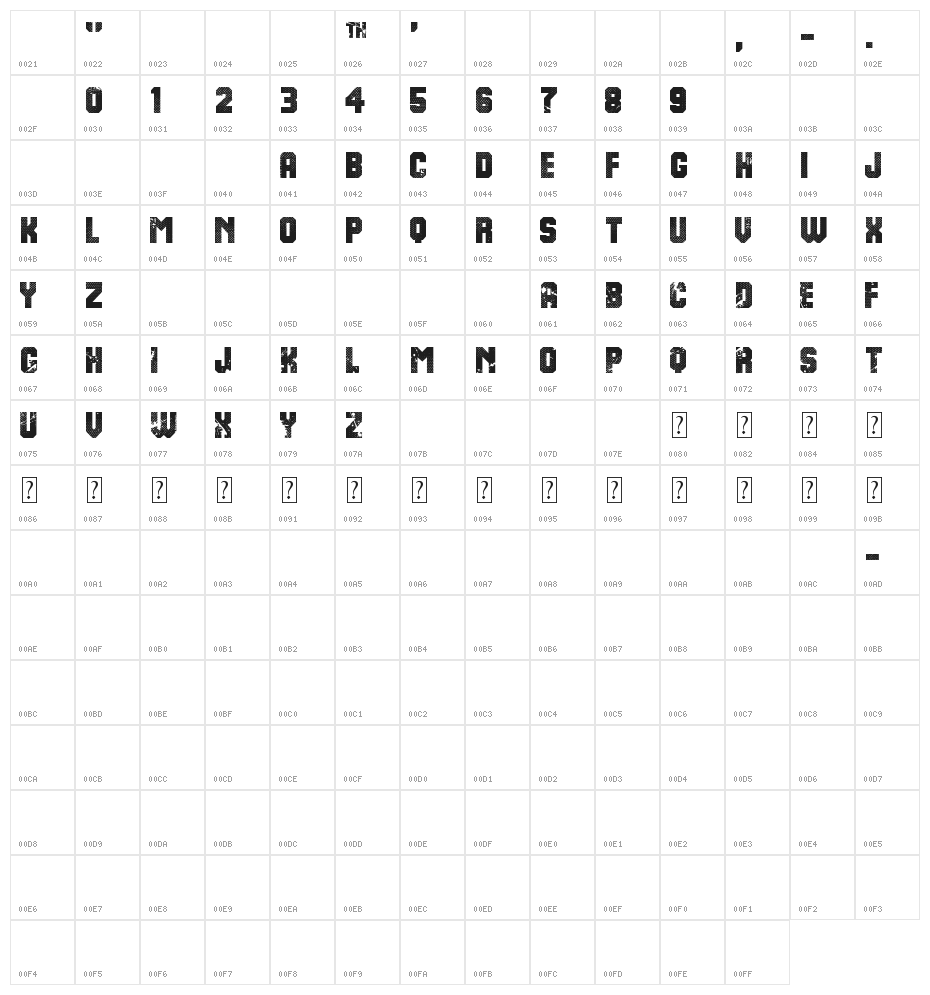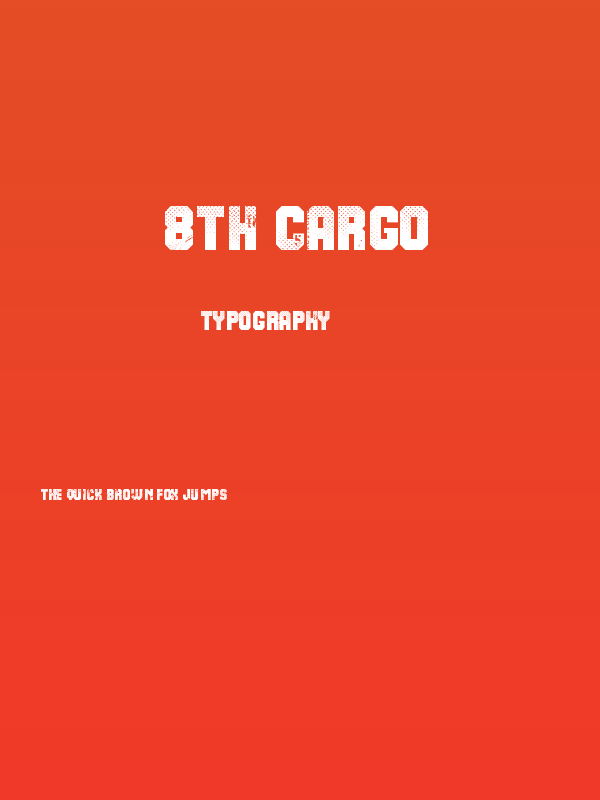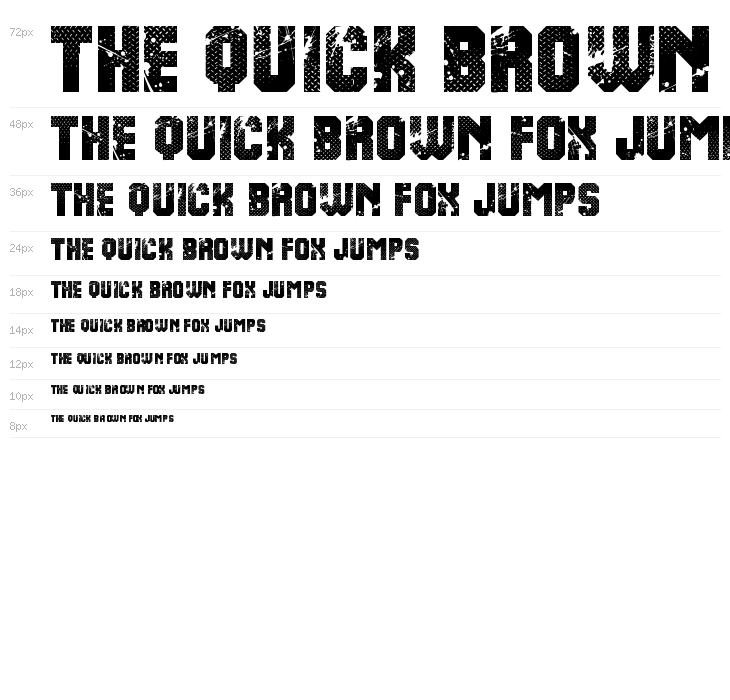
8th Cargo Font
✎ Stencil
| 分类 | Stencil |
| 整体风格 | Industrial, Grunge |
| 推荐项目 | Ideal for projects requiring a strong, industrial look, such as posters, album covers, branding for outdoor or adventure products, and urban-themed designs. |